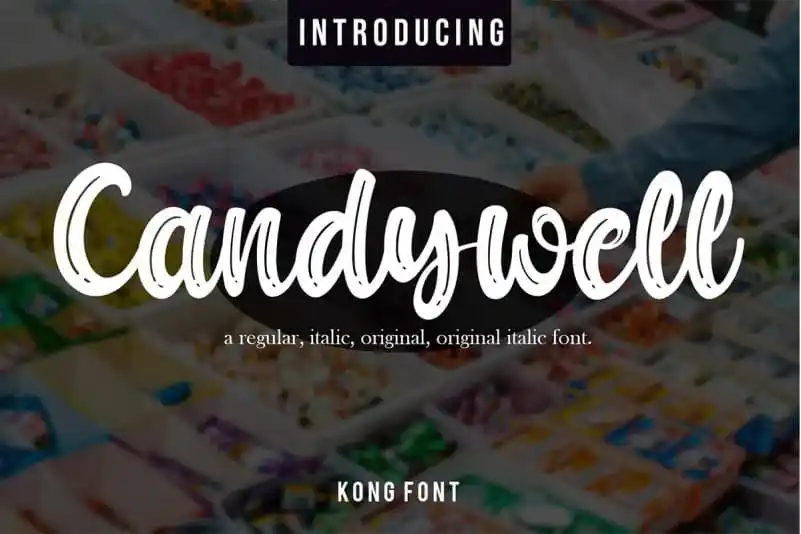
A Candywell Brush Font é uma excelente opção para aqueles que procuram uma fonte de estilo brush com alta qualidade e multifuncionalidade. Suas características suaves e expressivas tornam-a perfeita tanto para logotipos quanto para headlines, texto em letras grandes ou até mesmo para qualquer tipo de design onde seja necessário um charme delicado e versátil. Desenvolvida pela plataforma 99designs, essa fonte é a escolha ideal para quem deseja adicionar autenticidade e personalidade ao seu projeto gráfico. Com sua composição em estilo brush, Candywell Brush Font não apenas oferece uma aparência única, mas também um toque de brilho que enriquecerá qualquer layout ou design gráfico. Seja você designer web, publicitário ou ilustrador digital, essa fonte irá transformar seus trabalhos, adicionando o toque definitivo necessário para que eles sejam inesquecíveis e impecáveis.